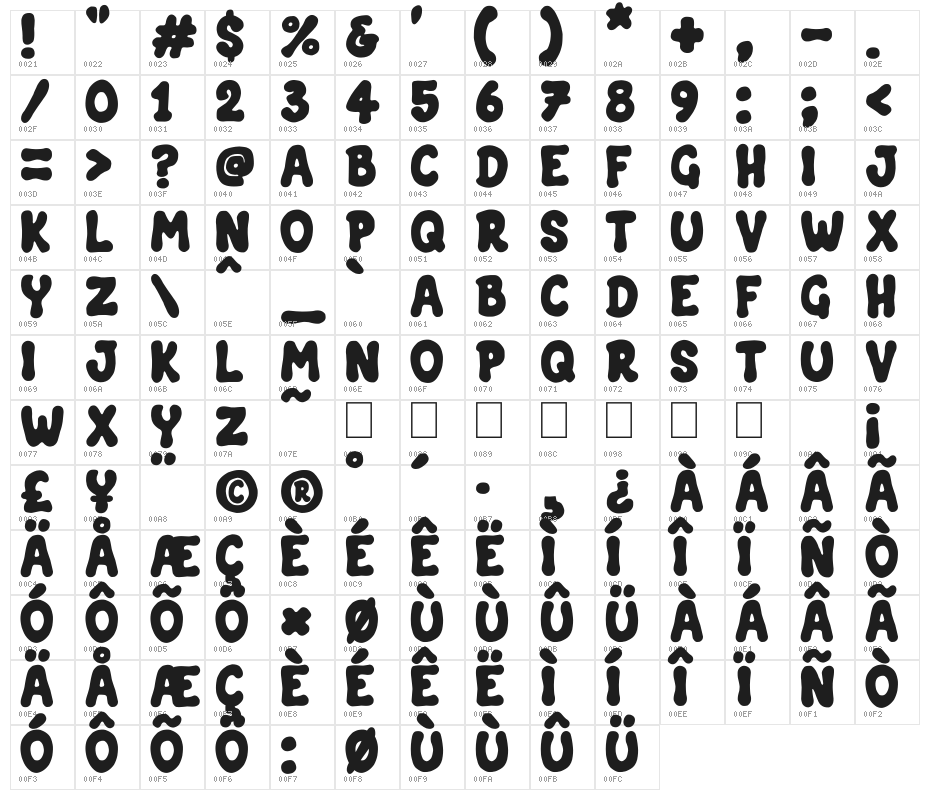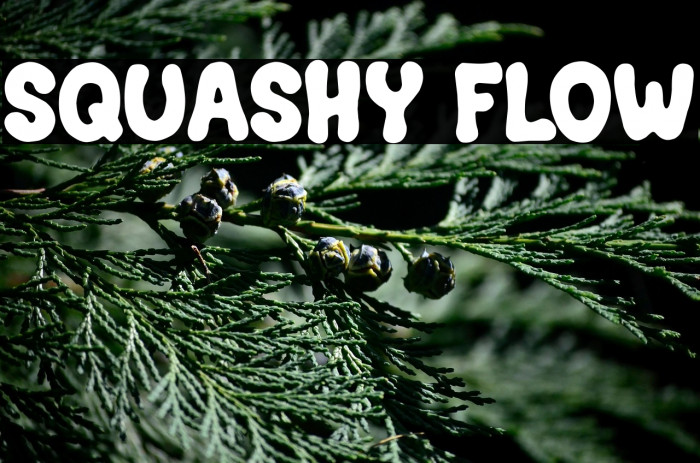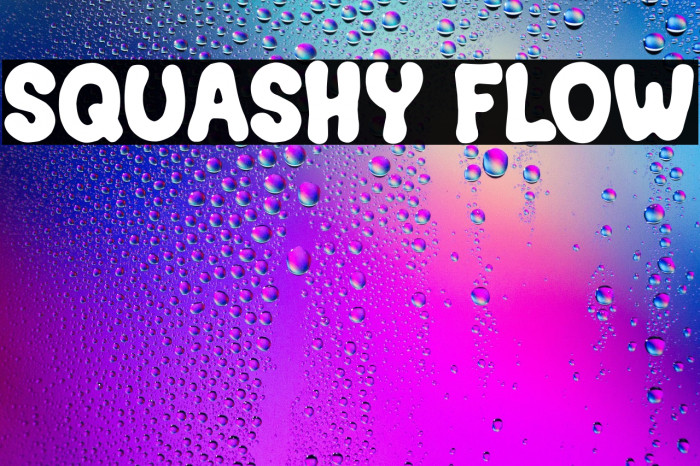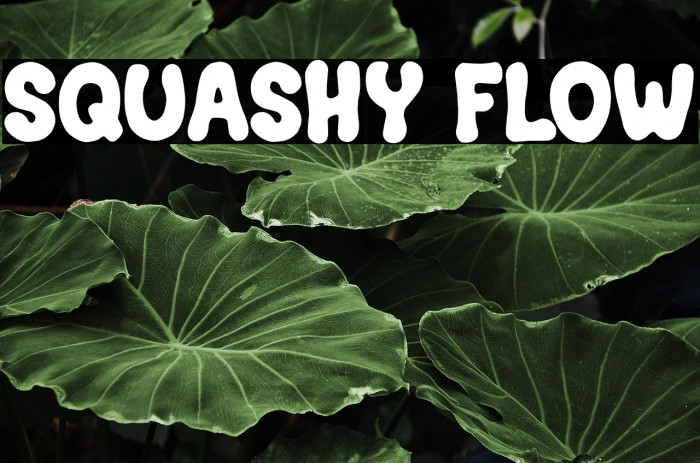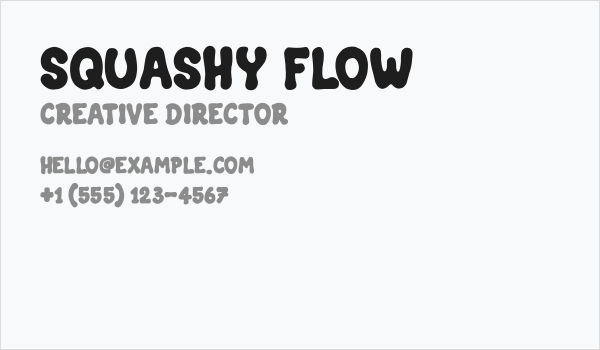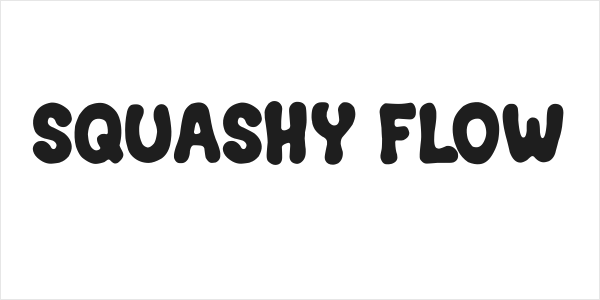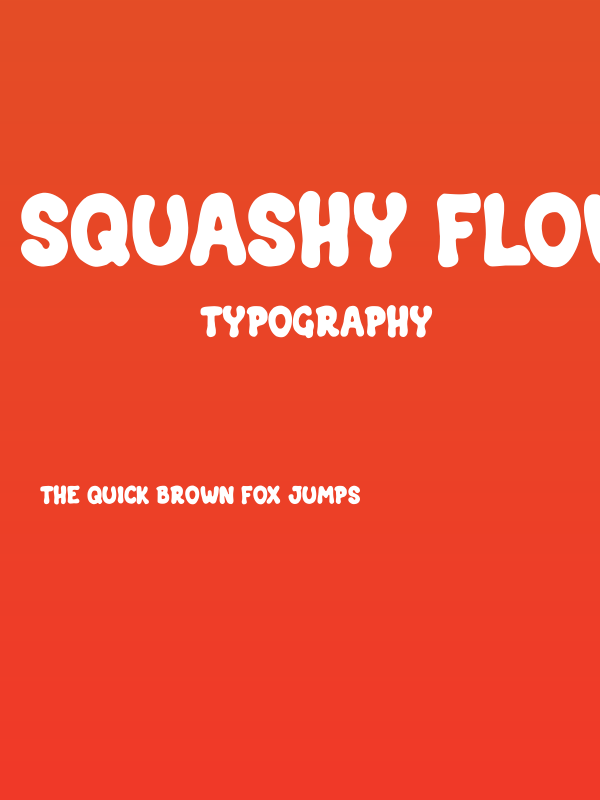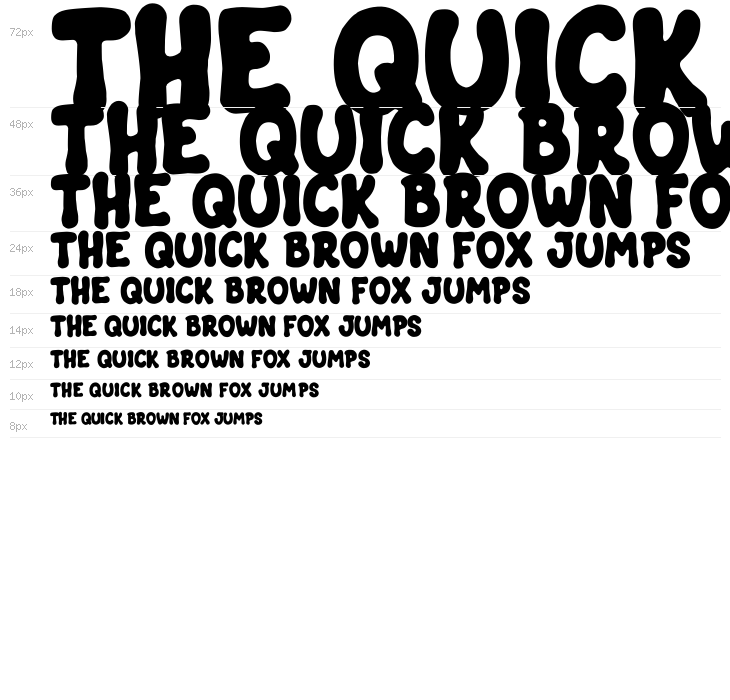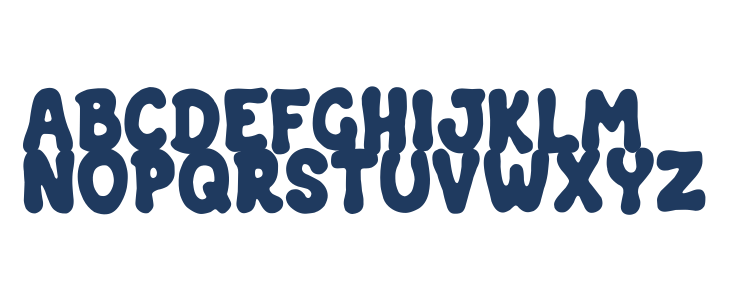
Squashy Flow Font
| Gesamtstil | Playful, Whimsical |
| Vorgeschlagene Projekte | Ideal for children's books, playful branding, event posters, and any design needing a fun, approachable feel. |